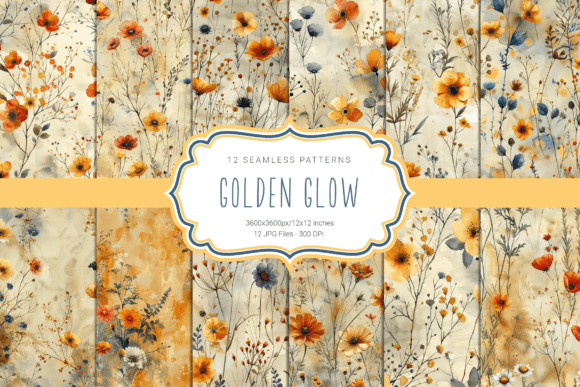
Golden Glow
Die richtigen Designelemente zu finden, kann eine Herausforderung sein, aber Golden Glow bietet eine außergewöhnliche Sammlung, die Ihre Arbeit sofort aufwertet.
Egal, ob Sie POD-Produkte (Print on Demand), Hochzeitseinladungen oder Social-Media-Grafiken erstellen, Golden Glow ist die ideale Wahl.